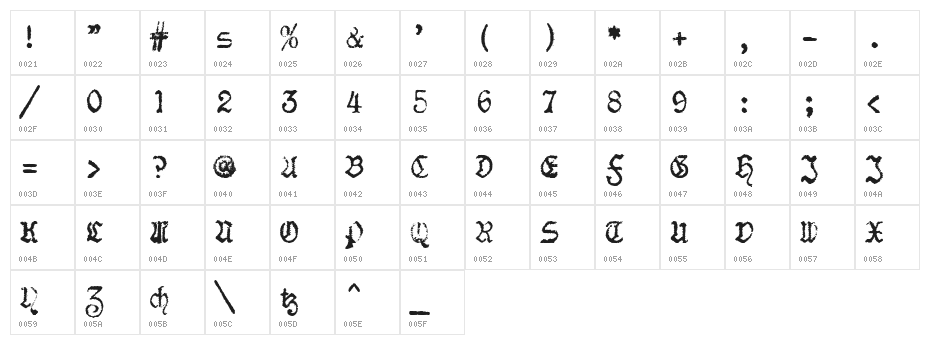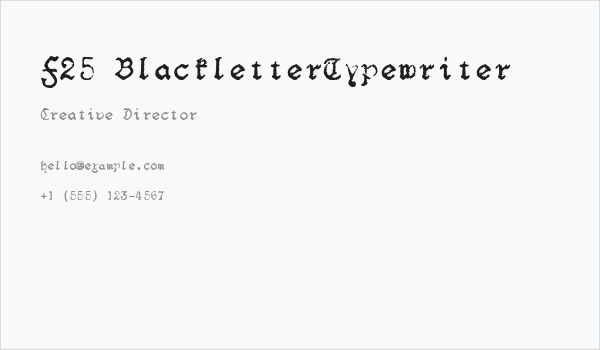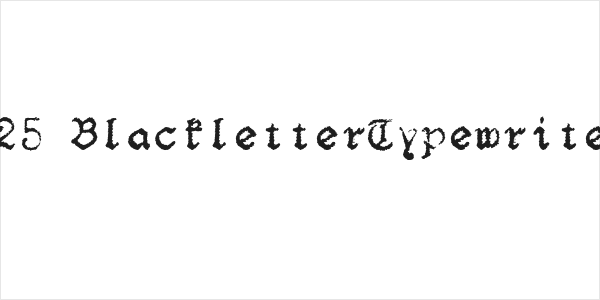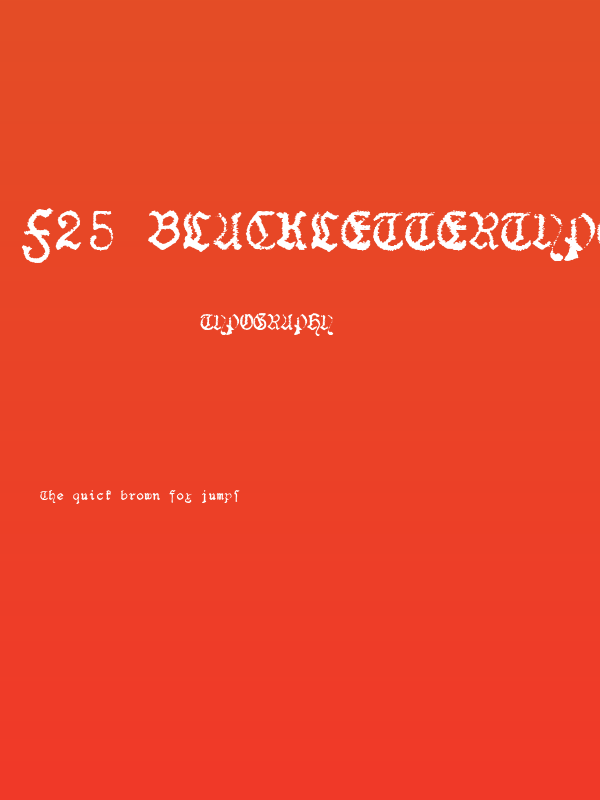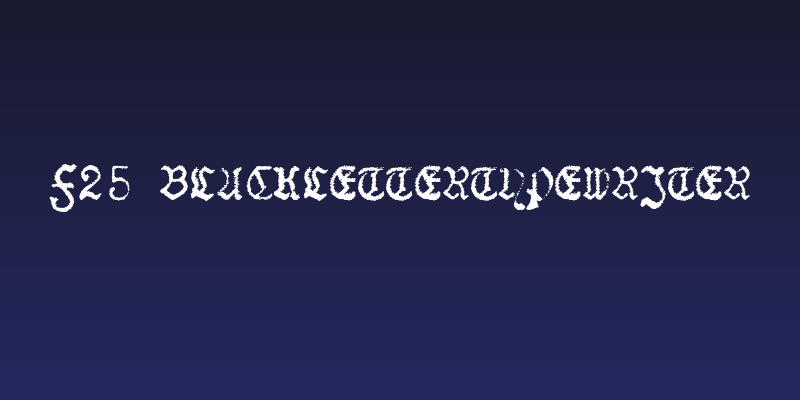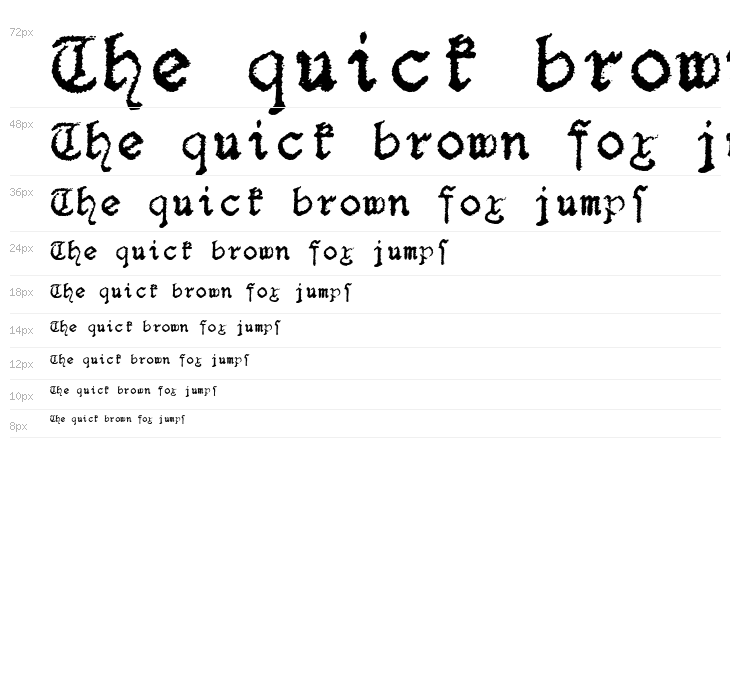
F25 BlackletterTypewriter Font
| Categorie | Typewriter |
| Caso d'uso | Headlines, Logos, Decorative text |
| Progetti proposti | Ideal for vintage-themed designs, historical documents, book covers, or any project seeking a classic and formal aesthetic. |